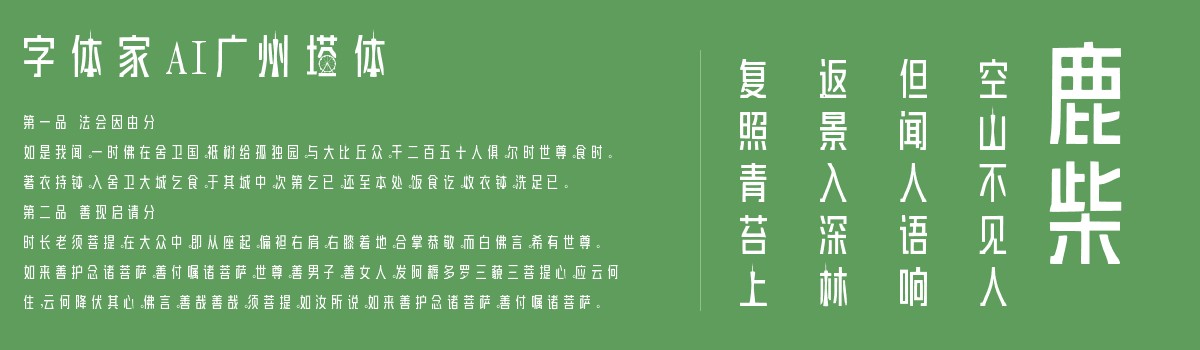
字体家AI广州塔体
这款字体确实很有趣!字体家AI神笔造字推出的广州塔体,通过将“竖”笔画改为广州塔的小蛮腰形状,使得字体不仅时尚,还充满了广州的独特文化元素。
广州塔,也被称为小蛮腰,是广州的地标之一,位于珠江边,为这座城市增添了许多现代气息。这种设计灵感,让广州塔体在艺术设计、平面宣传设计、网页设计和书法字帖等领域显得特别适合。
通过这种结合,字体不仅传递信息,也成为了一种视觉艺术,给人留下深刻印象。无论是本地企业还是国际品牌,如果想要突出地域特色,这种字体无疑是一个绝佳的选择。下次有机会,我一定要试试看用它来设计一些好玩的东西!